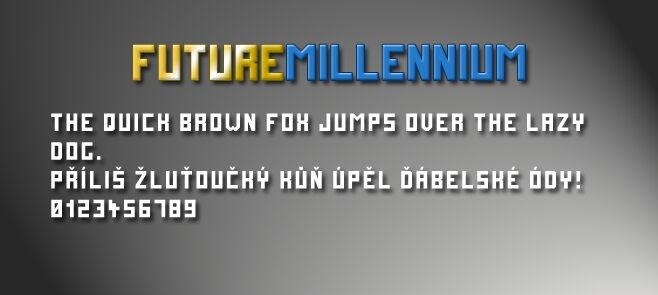
Future Millennium od Zdenka Gromnicy to darmowy techniczny krój pisma typu display, który wygląda, jakby został wykuty z litego bloku pikseli. Masywne pionowe linie, kwadratowe narożniki i ciasny, modularny światłorozstrój nadają każdemu słowu wyrazisty klimat sci-fi, niczym szyldy klubu nocnego na odległej stacji kosmicznej. Litery idealnie zazębiają się w sztywnej siatce, tworząc odważne czarne pasma, które natychmiast przykuwają wzrok.
Dzięki Future Millennium Twoje projekty nabiorą surowego, elektronicznego rytmu, który świetnie sprawdzi się w logotypach gier, ulotkach EDM, plakatach science-fiction, miniaturkach technicznych na YouTube czy w identyfikacji wizualnej wydarzeń. Ten darmowy font najlepiej prezentuje się w dużych rozmiarach i przy mocnym kontraście; połącz go z prostym geometrycznym bezszeryfowcem w tekście głównym i pozwól, by Future Millennium zdominował tytuły, przyciski i główne nagłówki.